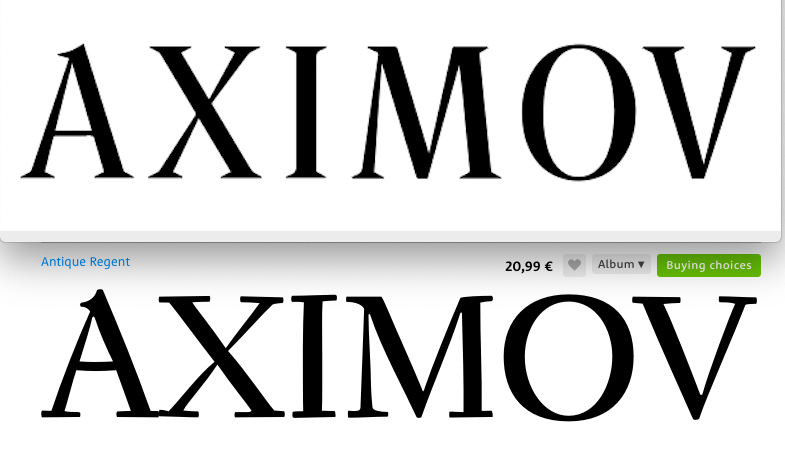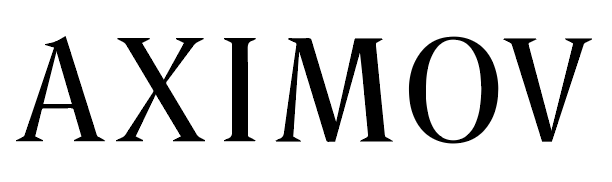
Auf der Suche nach diesem modernen Serifenfont
ich bin auch der Suche nach der für diesen Schriftzug verwendeten Schrift. Leider habe ich keine Hintergrundinformationen. Es ist ein Screenshot aus einer mehrere Jahre alten internen Präsentation bei uns im Grafikbüro, und niemand scheint sich an den Namen erinnern können. Nun bräuchte ich die Schrift – darf auch gerne was kosten! Freue mich über zweckdienliche Hinweise.
Danke für Deine Antwort. Die Antique Regent geht zwar in die richtige Richtung, aber die ist es leider nicht. Die Schrift in meiner Vorlage ist schmaler (X, O), die Serifen laufen spitz zu, und die Schenkel (M) sind nicht parallel …
Nein, Unsinn. Ist sie nicht – da habe ich zu schnell gepostet.